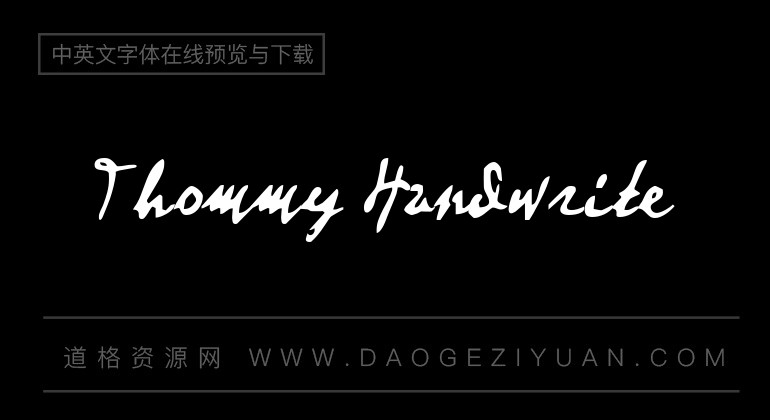
Thommy Handwrite 是一款手写字体,由著名的英国设计师 Thommy 所设计。它的特点是简洁、细腻、优雅,可以用于各种类型的设计作品,从博客、海报、网站、广告等等,都可以使用它来增加设计的视觉效果。它的字形多变,可以满足不同的设计需求,而且还可以调整字体的大小、颜色、字形等等,使得设计师可以根据自己的需求调整字体,以达到最佳的视觉效果。内容介绍
Thommy Handwrite是一款非常不错的手写艺术字体,具有很好的视觉感,适合于文化类的宣传设计、商业类品牌的广告和产品包装设计以及个性化文字排版等较多场景。